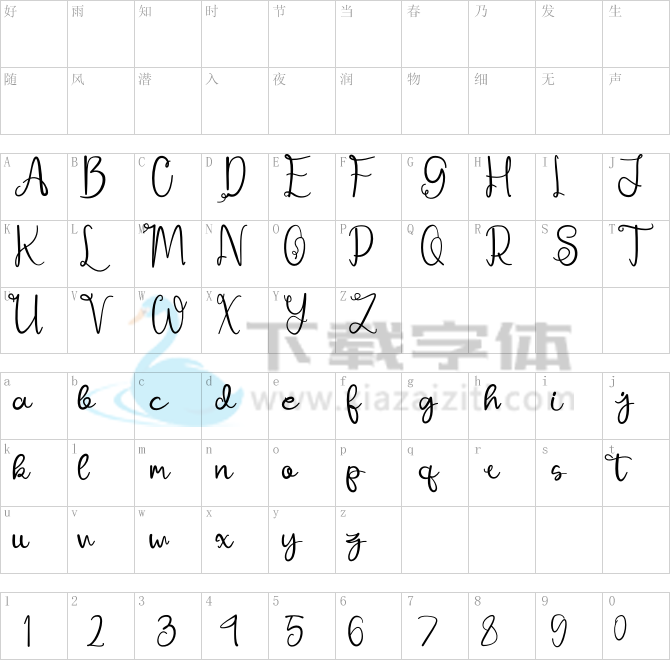
Ajuslly.otf字体下载,这款字体结构工整、笔画清晰,兼顾美观与易读性,适用于标题、正文、海报、包装、LOGO 等多种场景。字形优雅稳定,风格百搭耐看,适配日常排版与创意设计,让文字呈现更舒适、更具质感。Ajuslly.otf字体下载一笔一画,皆是细节,以均衡的比例、流畅的线条打造舒适视觉体验,字形端正大气,风格简约现代。无论是商业设计、品牌宣传还是日常排版,都能轻松驾驭,让文字更有格调与力量。Ajuslly.otf字体下载字体下载。